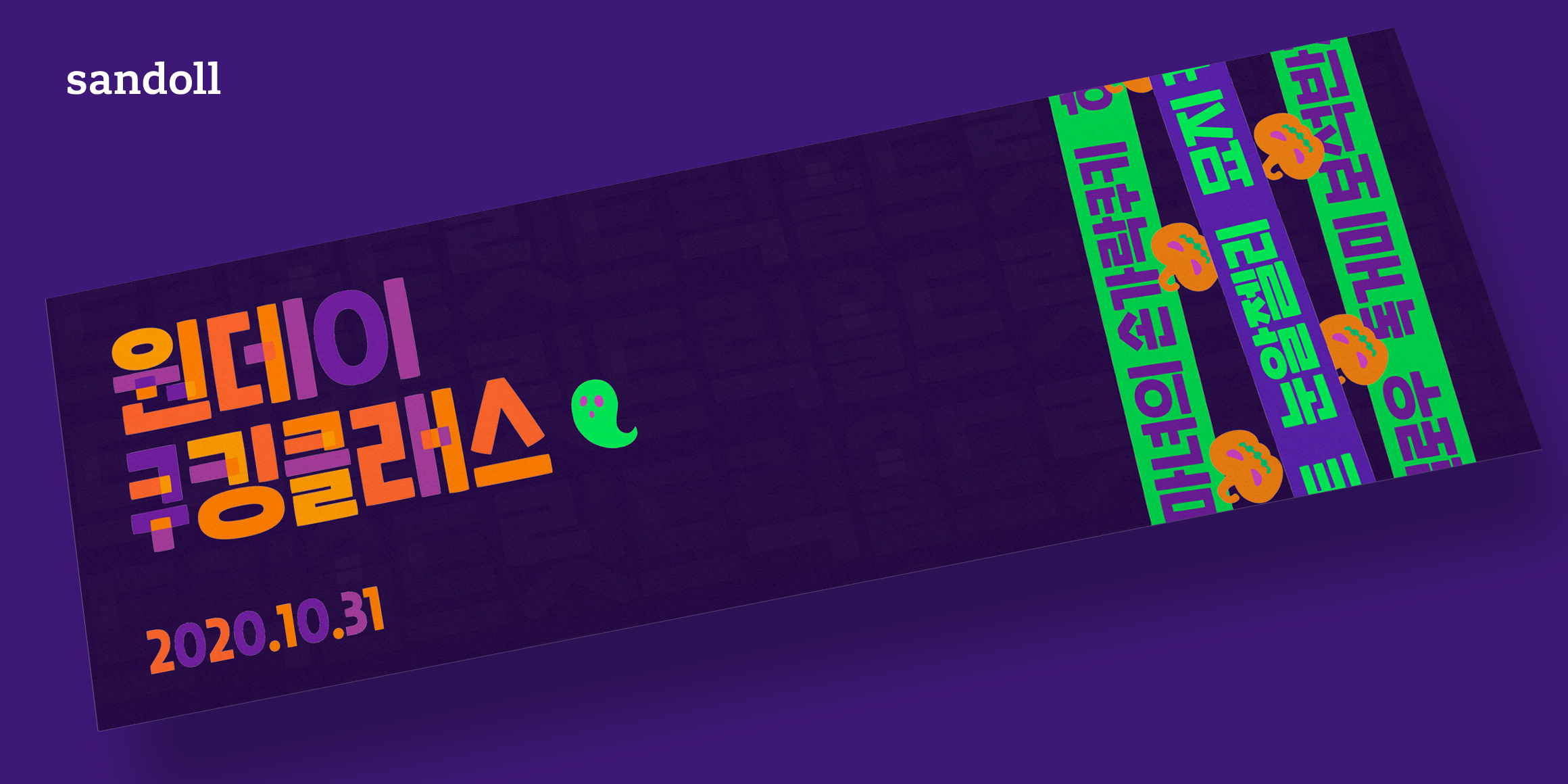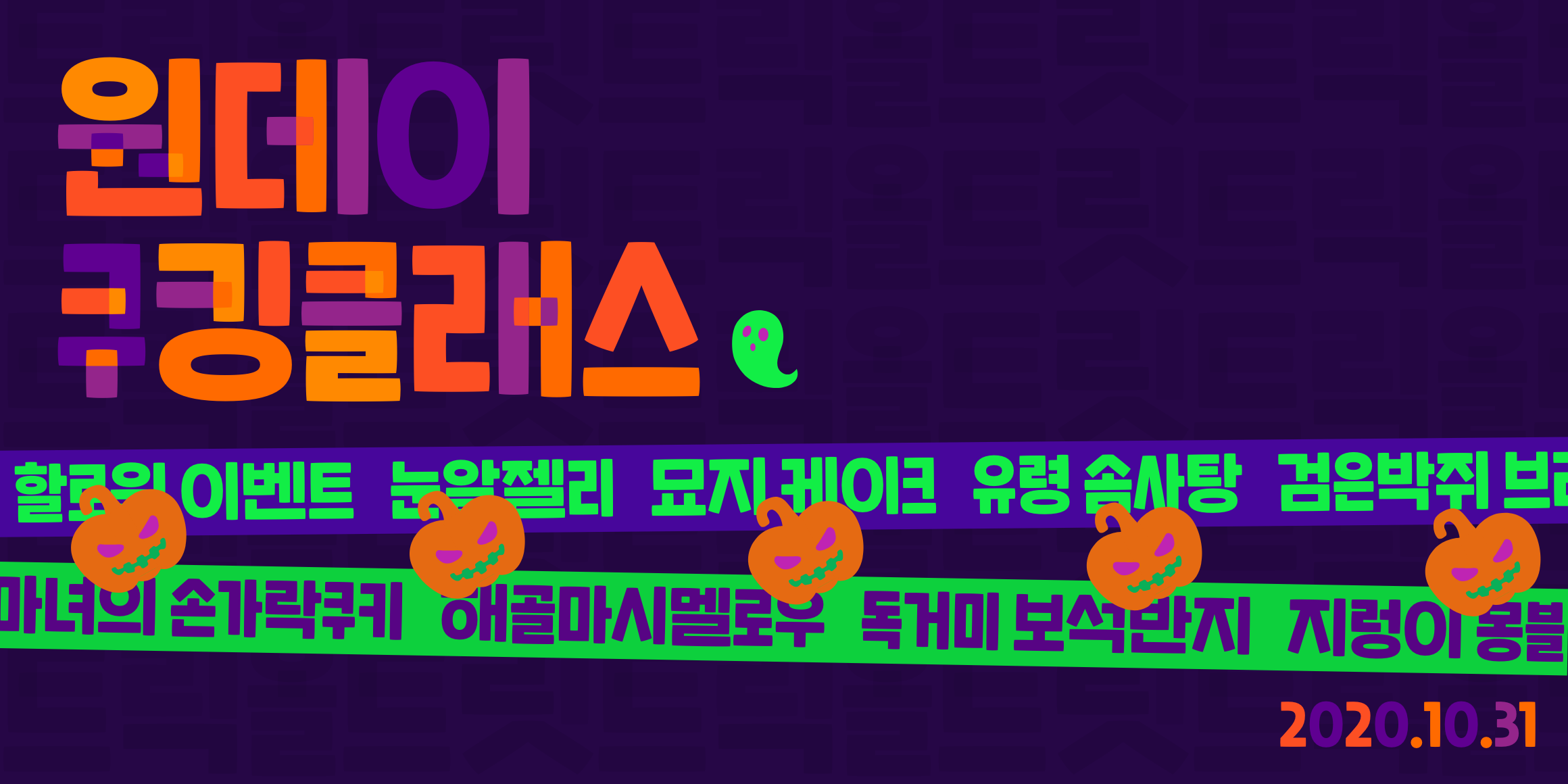
Mono
Neon
Pastel
Pumpkin
Violet
Xmas
산돌의 인기폰트인 '산돌 호요요'를 바탕으로 총 6가지의 스타일을 제작했습니다.
글자의 모양 뿐 아니라 색상 데이터가 포함되어있어 별도의 수정 없이도 컬러나 질감이 입혀진 폰트를 사용하실 수 있습니다.
산돌 호요요 Color를 통해서 보다 편리한 타이포그래피 작업을 진행해보세요!